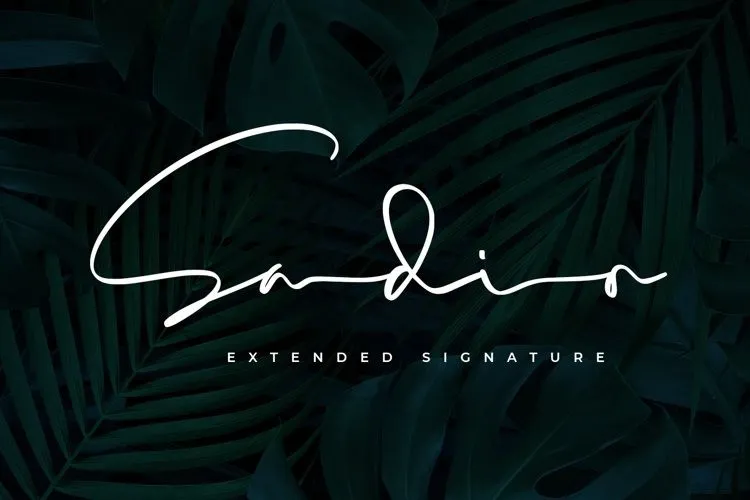
A Sadio Font é uma elegante fonte escrita à mão que surgiu do Abo Daniel Studio, ideal para criar logotipos ou textos de destaque. Especialmente concebida para dar um toque único e distintivo a marcas e carimbos, a fonte é perfeita para o branding da sua empresa, bem como para cartões de visita e assinaturas profissionais. Uma vez que essa fonte foi criada especificamente para logotipos, ela não é recomendada para textos secundários ou conteúdo principal. Contudo, a Sadio Font oferece um toque sofisticado e único em qualquer aplicação onde desejar introduzir uma identidade visual de alta qualidade. Esta elegante fonte escrita à mão traz um charme especial aos seus projetos, criando uma presença única que destaca o seu trabalho ou marca personalizada no mercado.